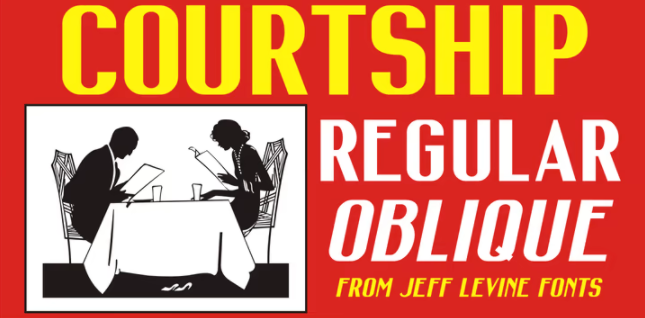
Название, написанное от руки в стиле модерн на нотах композиции 1909 года "If the Wind Had Only Blown the Other Way", послужило основой для "Courtship JNL", которая доступна в обычной и наклонной версиях.